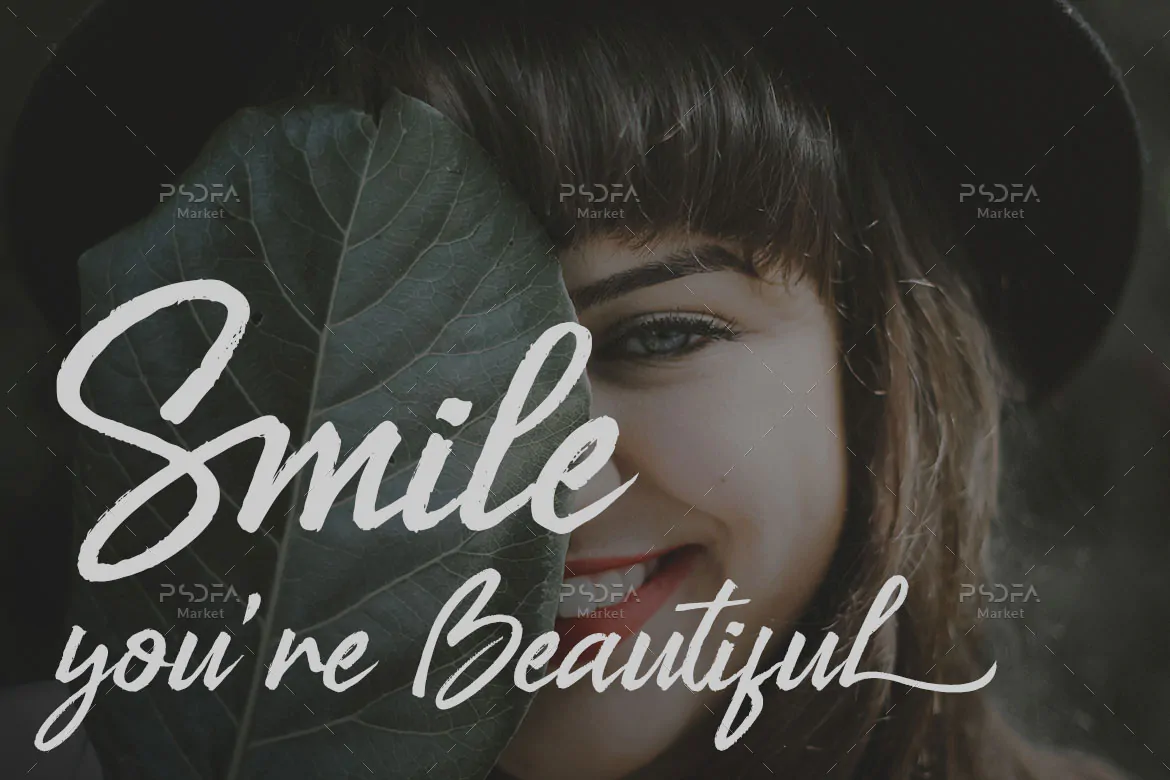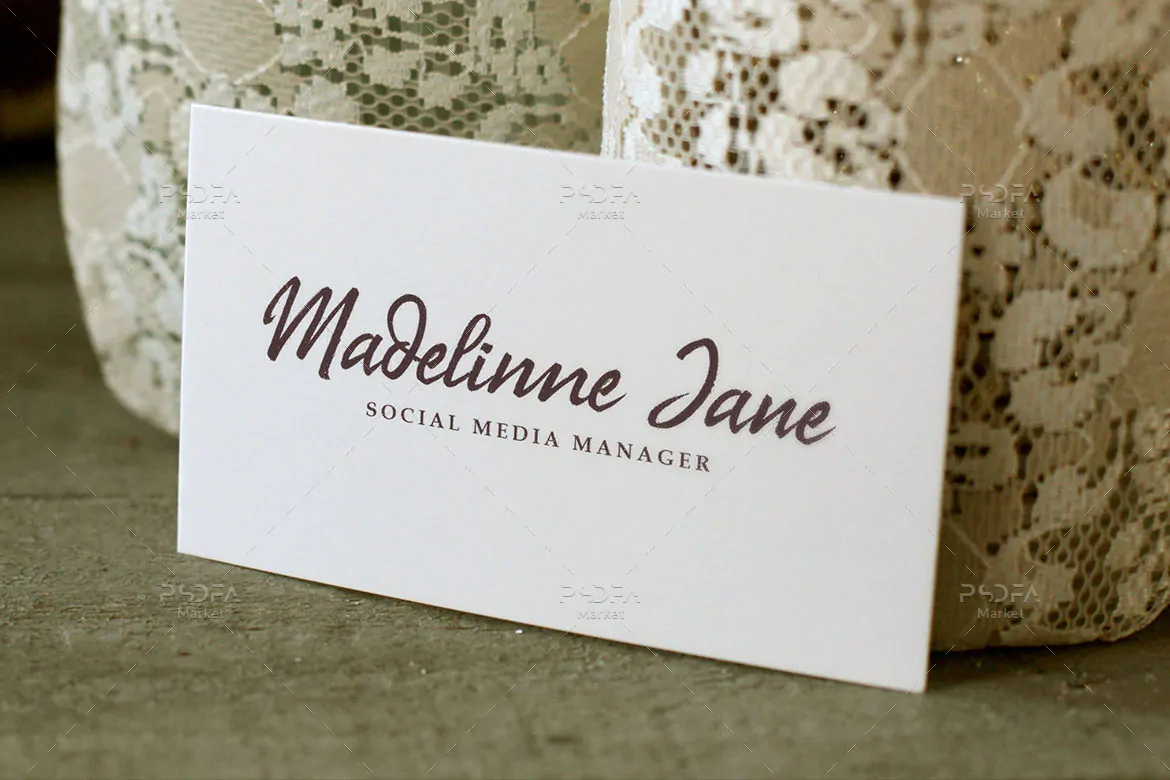
فونت امضایی بافت دار Bill Smith
فونت امضایی بافت دار
فونت امضایی بافت دار Bill Smith یک اسکریپت فونت انگلیسی زیبا است که مناسب جهت استفاده در طرحهای گرافیکی مختلف به خصوص طراحی انواع پوستر میباشد. فونت Bill Smith با وزن معمولی طراحی شده است که میتوان از آن در طراحی انواع کارت، پوستر، بسته بندی محصولات، آرایشی و بهداشتی، لوازم التحریر و … استفاده نمود.